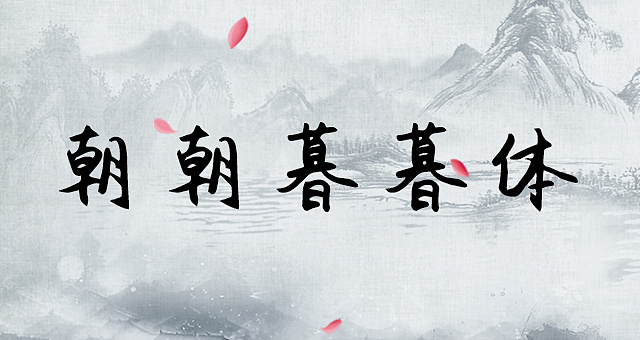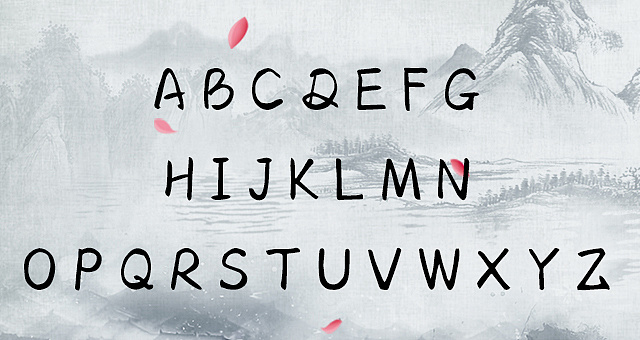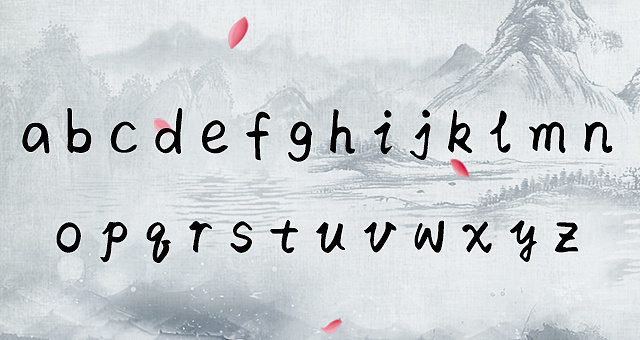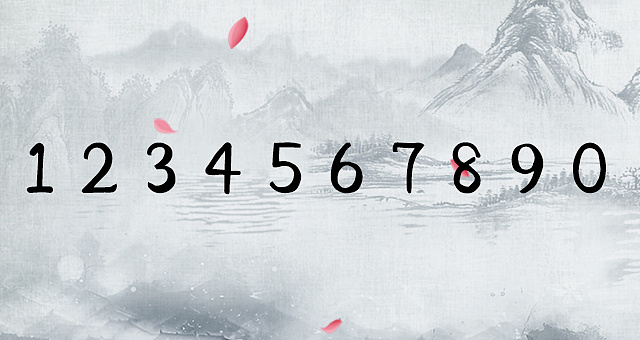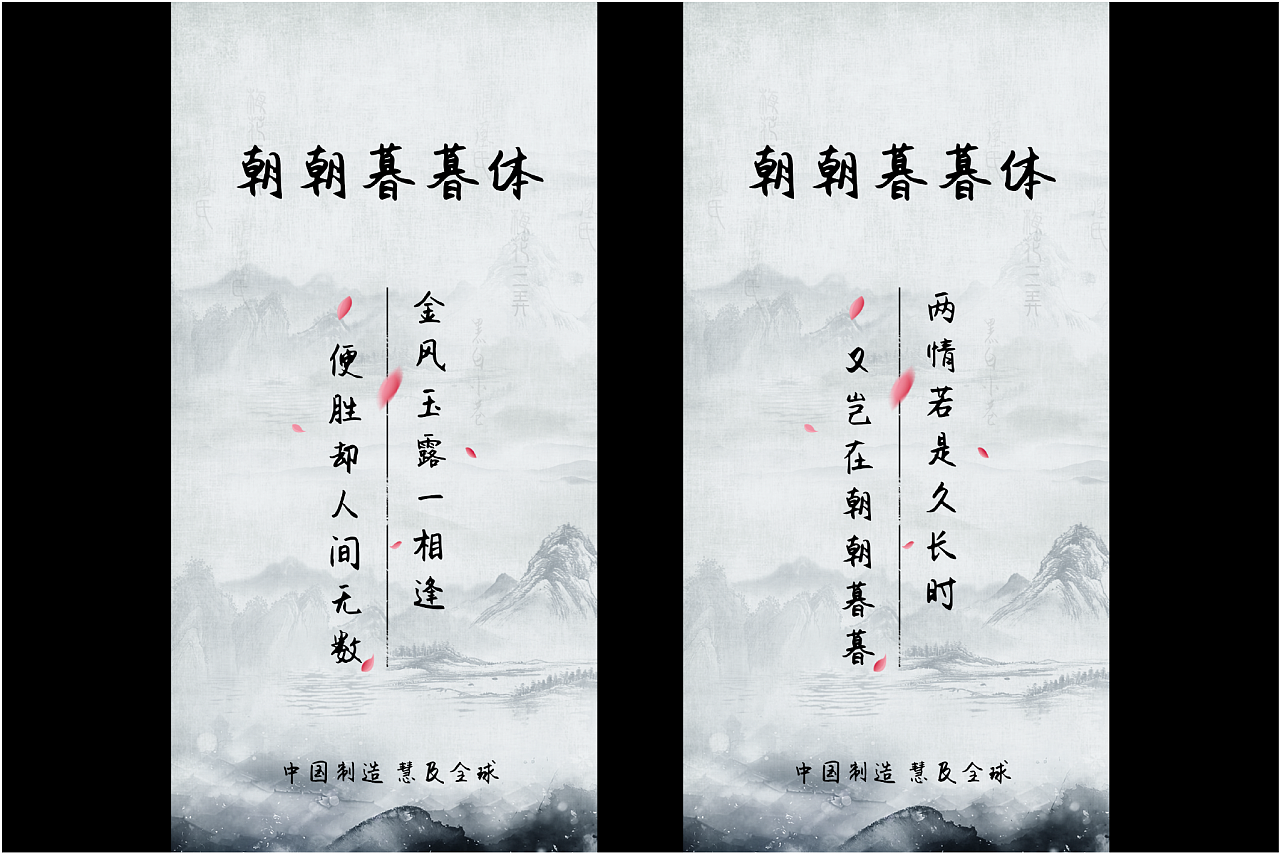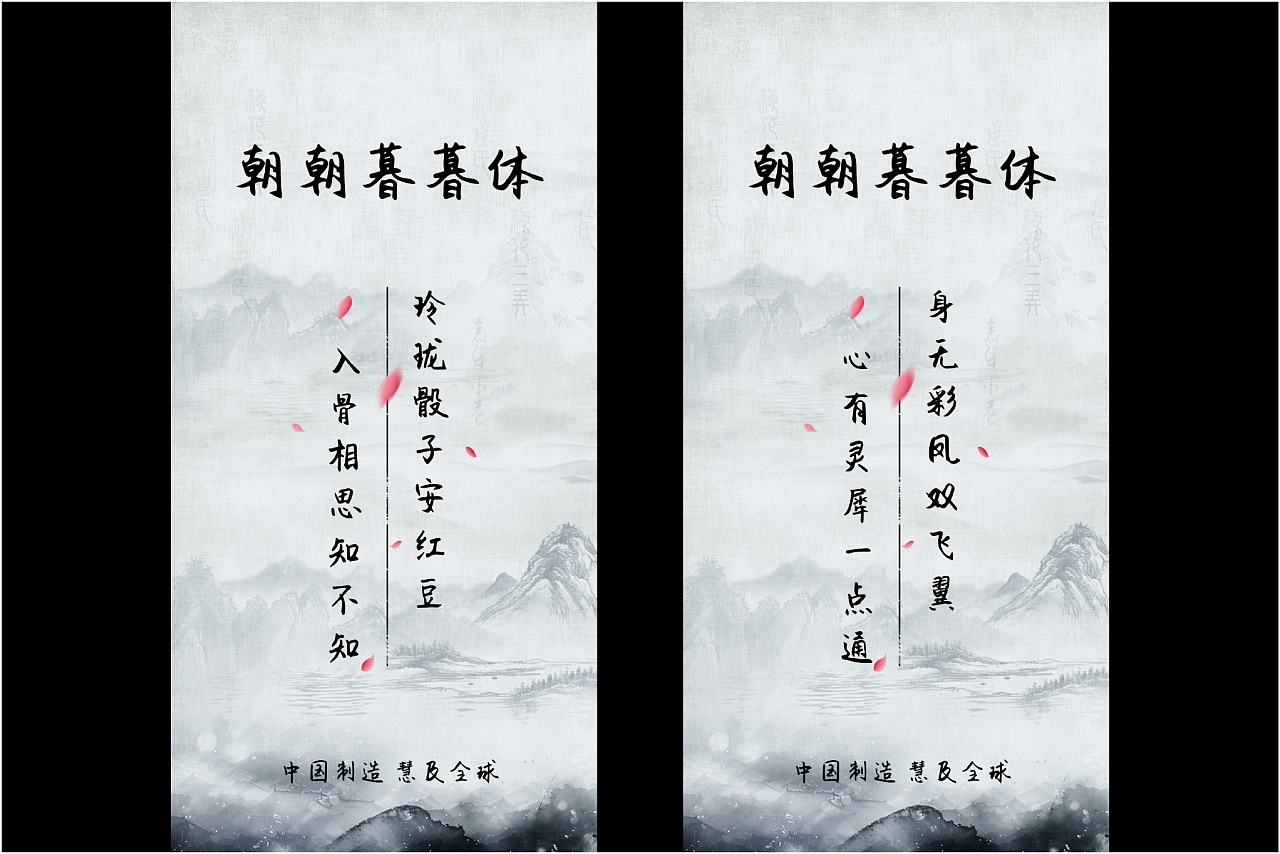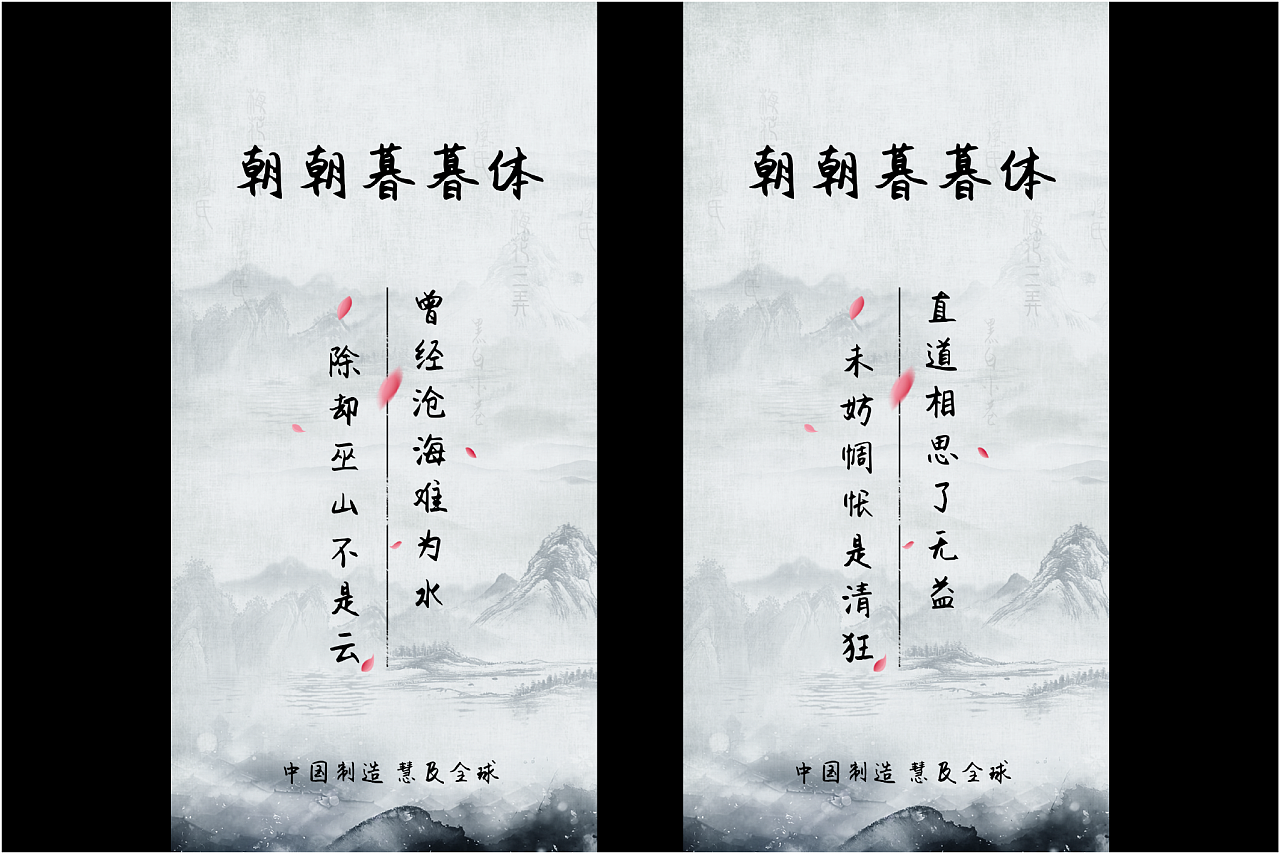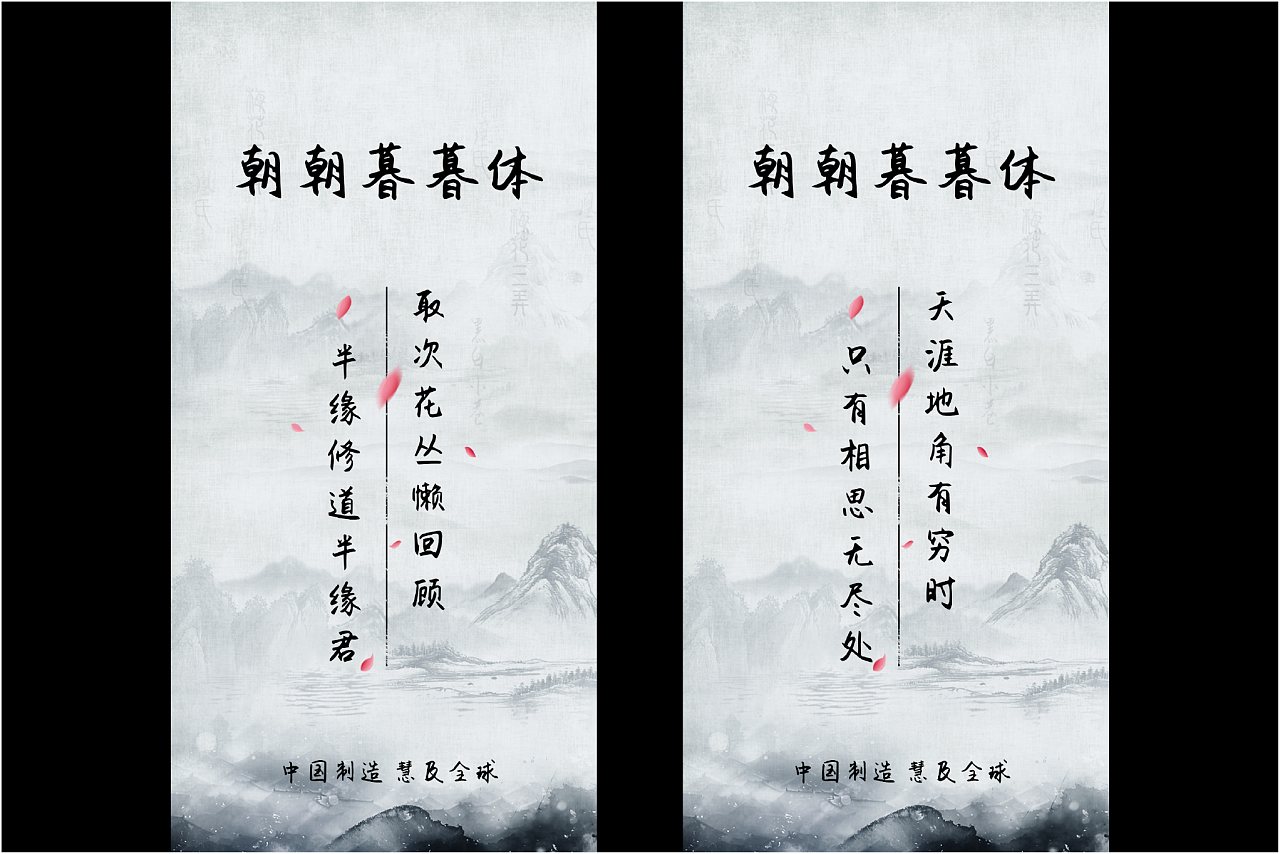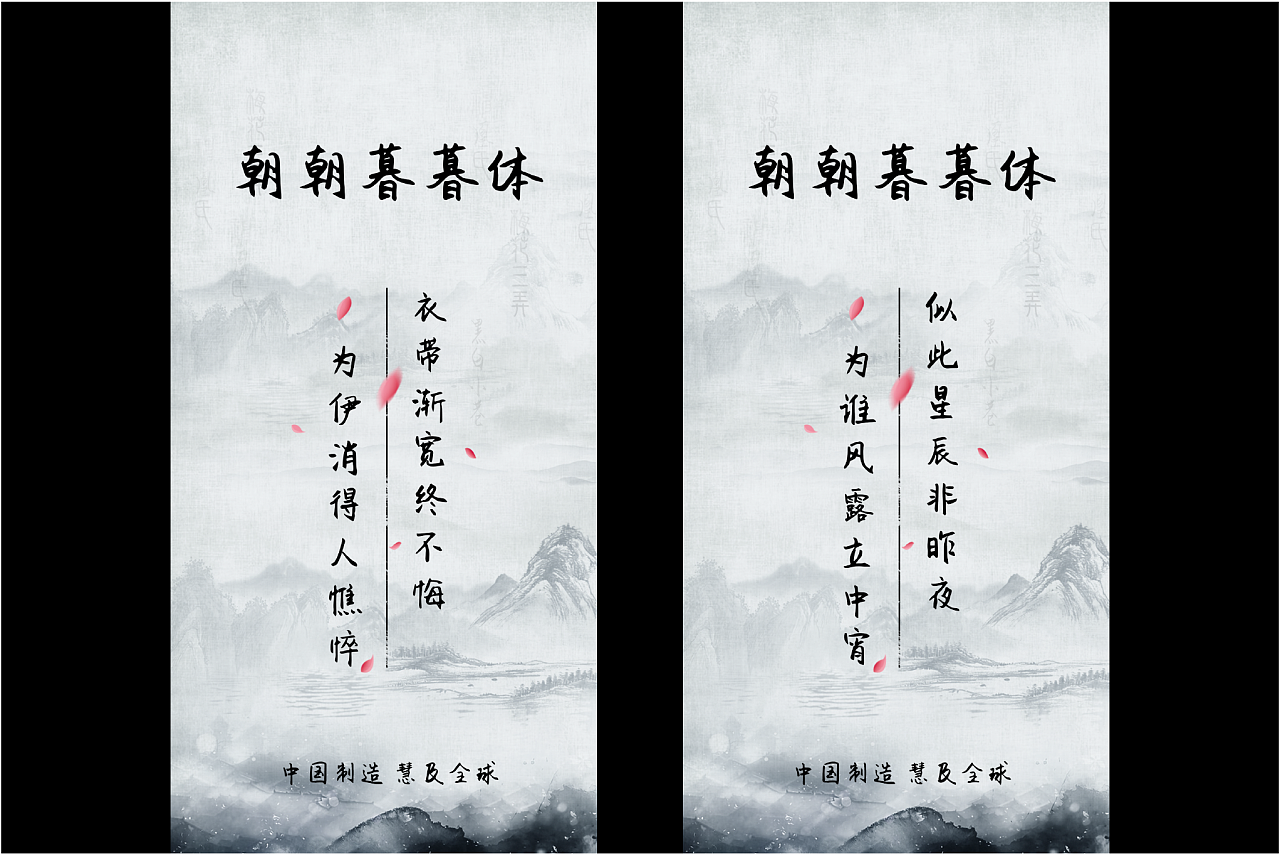
朝朝暮暮體 詳情頁(yè)
字體名稱(chēng): 朝朝暮暮體
朝朝暮暮體
朝朝暮暮體介紹
手寫(xiě)字庫(kù)字體(含漢字6763個(gè),符號(hào)字母若干)
作者:潘好
朝朝暮暮體為毛筆書(shū)寫(xiě)字體,字形寫(xiě)意,結(jié)構(gòu)放松。適用于漫畫(huà)、書(shū)刊、品牌廣告和產(chǎn)品包裝設(shè)計(jì),以及社交網(wǎng)絡(luò)的個(gè)性化用字。
字母和數(shù)字部分
字體字形應(yīng)用及展示